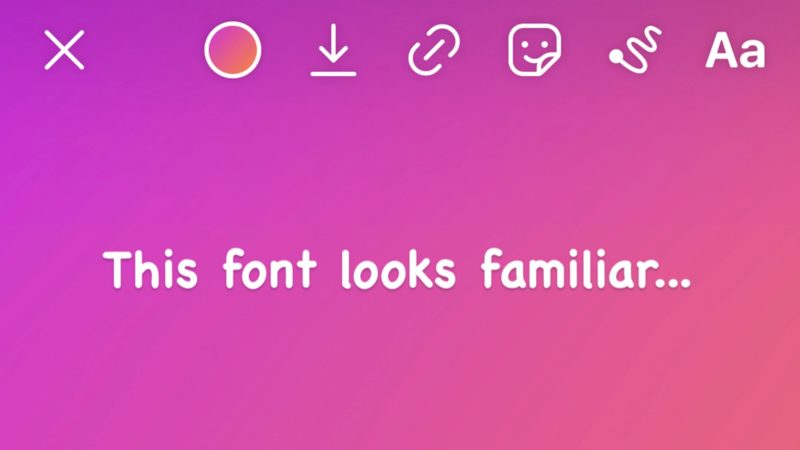
Come avere i NUOVI FONT su Instagram (anche Comic Sans)
Arriva il Comic Sans su Instagram e altre nuove scritte: come avere i font aggiuntivi all’interno delle storie. Guida per avere TUTTI i nuovi FONT su Instagram
Come avere nuovi font Instagram
Grandi novità per Instagram, che non smette mai di stupirci.
Oggi, invece, andiamo a scoprire un'altra interessante novità appena lanciata dal social network, cioè la possibilità di usare nuovi font e scritte nelle storie.
Proprio così: a sorpresa, con l'ultimo aggiornamento che è in fase di rilascio, su Instagram sono arrivati tantissimi nuovi font, tra i quali compare anche l'amato/odiato Comic Sans.
Se anche tu vuoi usare il Comic Sans per scrivere nelle storie Instagram, non perdiamo tempo e vediamo come fare. Ti dico subito che la procedura è abbastanza elementare e richiede davvero pochissimo tempo.
Come cambiare font Instagram (anche Comic Sans)
• all’interno di questa sezione trovi ora nuovi font, che ora salgono a 9, tra cui il Comic Sans (è il sesto scorrendo i caratteri disponibili da sinistra verso destra)
• chiudi Instander e riaprilo
• vai nelle Storie e controlla che i nuovi font siano stati attivati
Facile, vero? Adesso sei pronto per scrivere con altri font su Instagram e potrai notare che sono comparsi anche tutti quelli che prima non erano presenti.
Perché Instagram ha introdotto il font Comic Sans?
Instagram ha una buona ragione per aver scelto di aggiungere un carattere simile a Comic Sans.
Come sottolinea Mashable, il Comic Sans è considerato uno dei caratteri più facili da leggere per le persone con dislessia. L’irregolarità di ogni singola lettera rende le parole più facili da analizzare.
Ogni volta che uno sviluppatore può rendere il proprio prodotto più accessibile, è ovviamente una buona scelta.